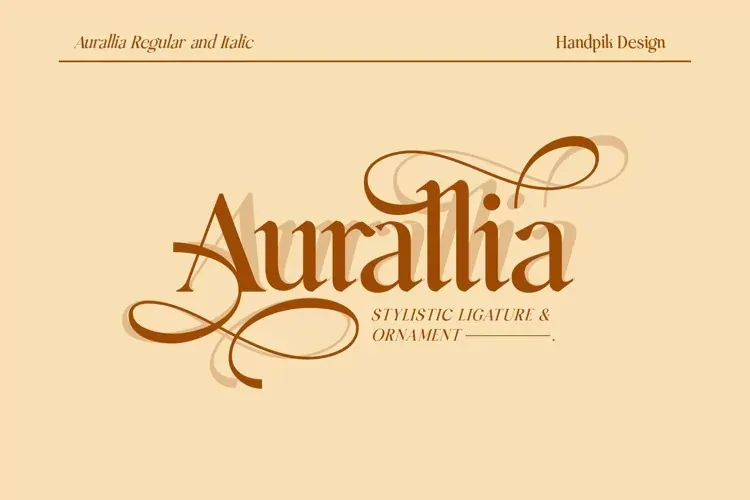
A Aurallia Font é uma elegante escolha para aqueles que buscam graciosidade em cada letra. Ela surge do talento sofisticado do designer handpik na 99designs, trazendo um estilo serífero e atraente. As letras deste tipo de fonte deixam uma impressão forte, perfeitamente adaptada para dar efeitos memoráveis aos seus projetos gráficos. A Aurallia Font não é apenas uma elegância ao primeiro olhar; ela também se destaca em um estilo luxuoso sem comprometer a simplicidade estilizada que tanto agrada. Sua feminina presença permite que você use esta fonte em designs de alta qualidade, enquanto seu preço acessível permitirá que você obtenha-a imediatamente. É uma escolha inteligente para aqueles buscando um toque elegante e sofisticado sem se comprometer com altos custos.